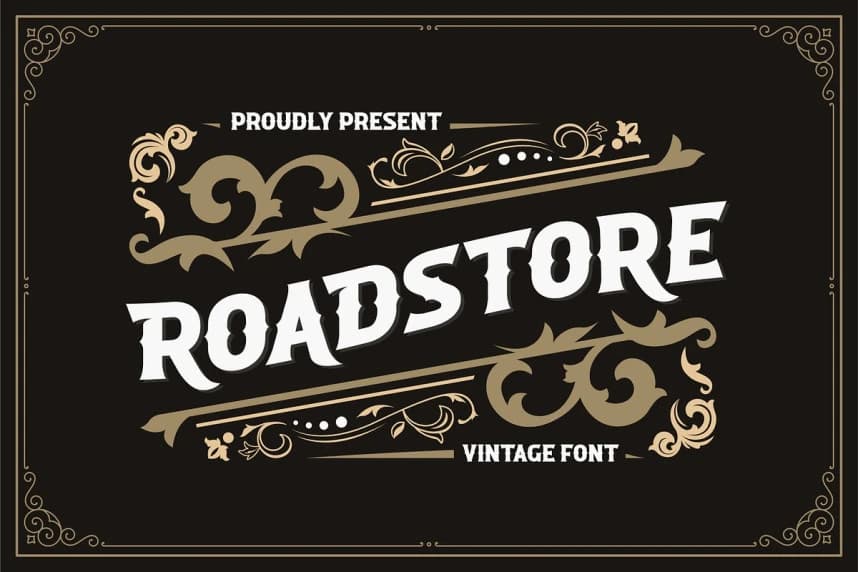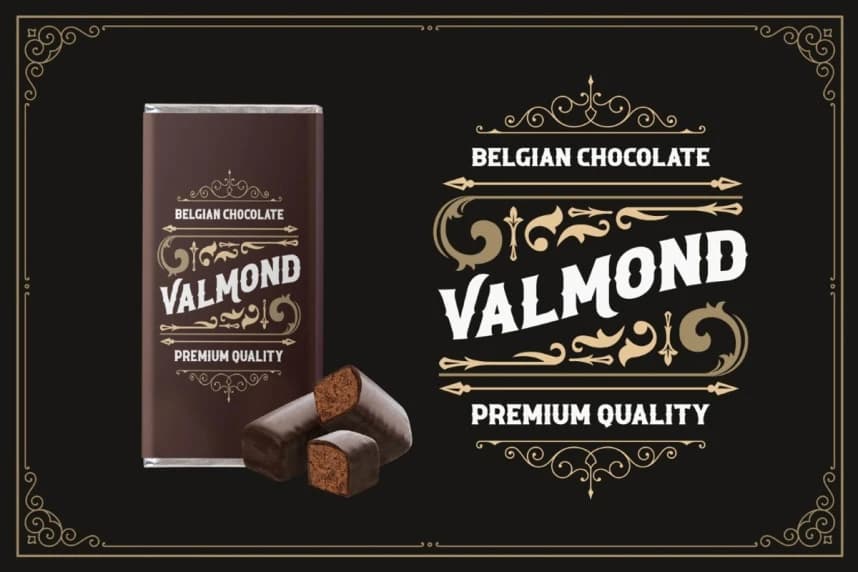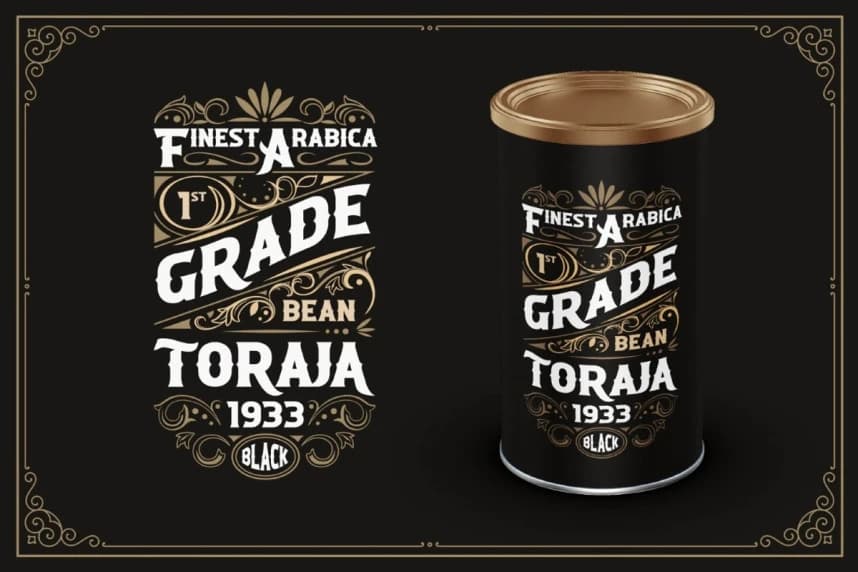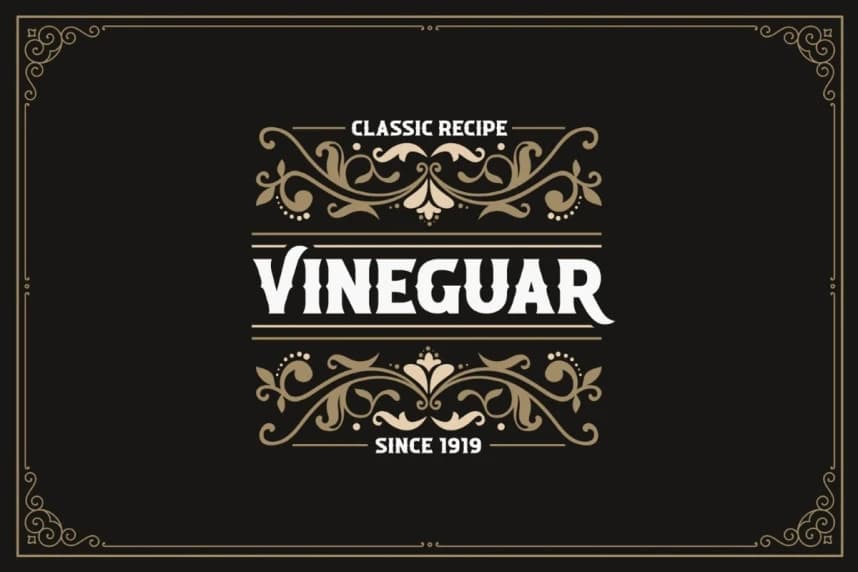
Roadstore Font
ROADSTORE Font: Vintage tatta benzersiz bir font; logotipinizi daha ilgi çekici hâle getirebilir. Özel alternatif gliflere sahip en iyi vintage font ve çok dilli destek. Dekoratif sanatlar ve mimarlık hareketinden esinlenilmiştir.
ROADSTORE Font A benzersiz bir yazı tipidir ve vintage tadıyla logotipinizi daha ilginç hâle getirebilir. Özel alternatif gliflerle ve çok dilli destekle En İyi Vintage yazı tipi. Dekoratif sanatlar ve mimarlık hareketinden esinlenmiştir.